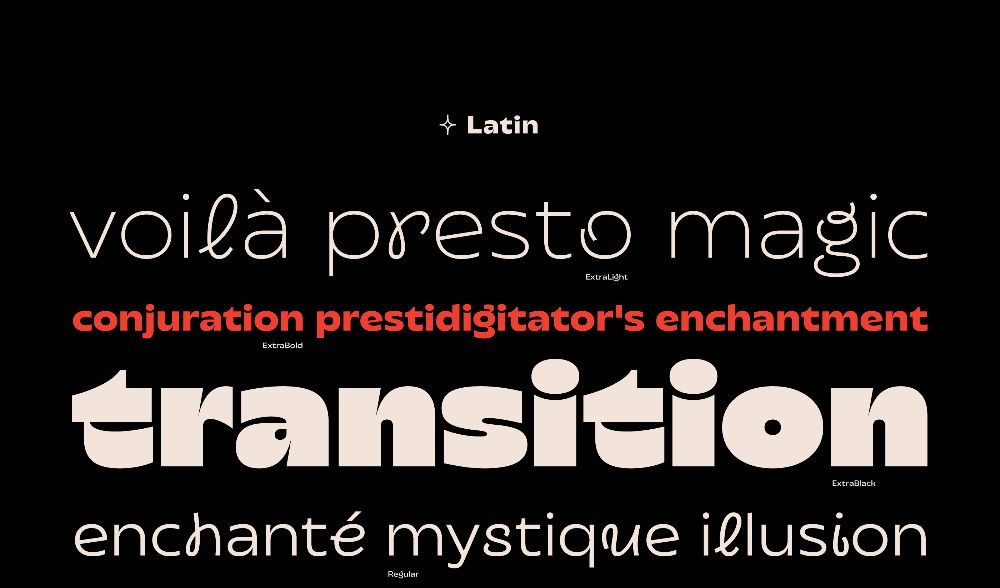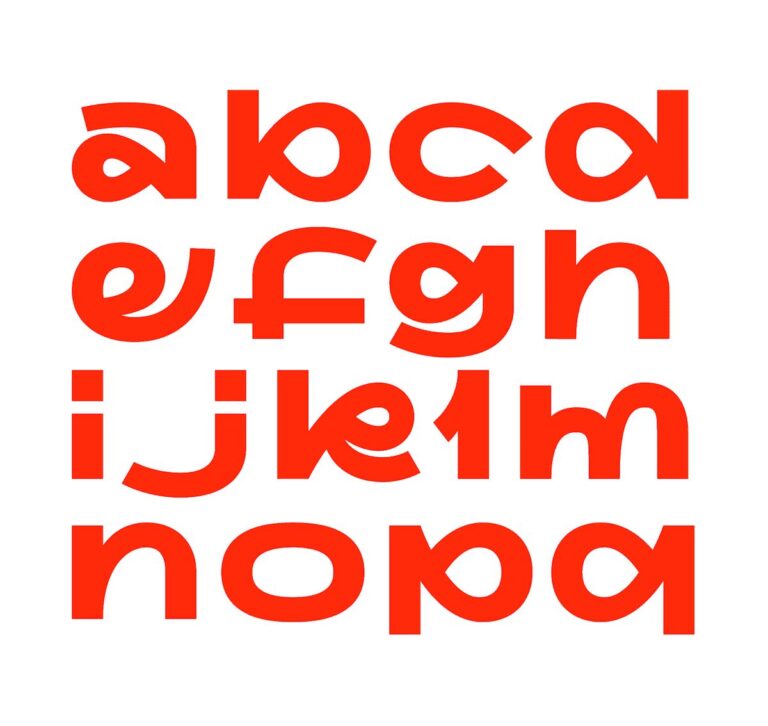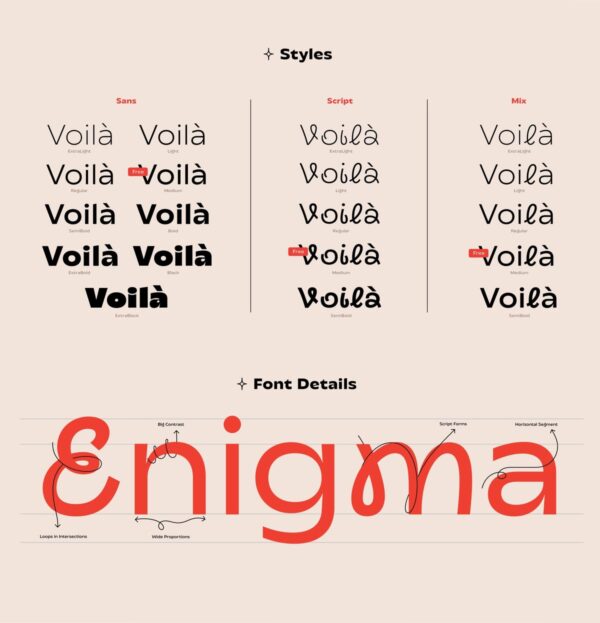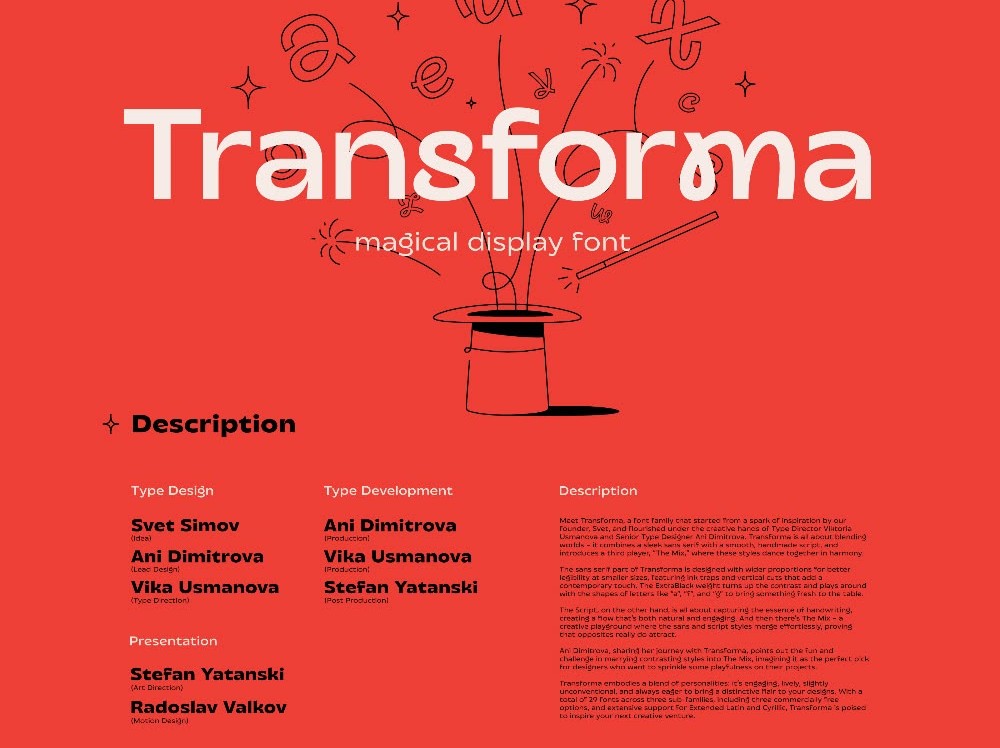
Transforma font family là một hệ thống phông chữ đồ sộ và linh hoạt, được thiết kế để đáp ứng nhu cầu sáng tạo đa dạng từ phong cách hiện đại, tối giản đến nghệ thuật bay bổng. Việc sở hữu trọn bộ Transforma font family Việt hóa giúp các kiến trúc sư và nhà thiết kế dễ dàng đồng bộ hóa ngôn ngữ hình ảnh cho các hồ sơ dự án, phối cảnh kiến trúc hay bộ nhận diện thương hiệu công trình.
Đặc tính thẩm mỹ và cấu trúc của Transforma font family Việt hóa
Điểm lôi cuốn đặc trưng của dòng phông này chính là sự tích hợp giữa nhiều nhánh phụ trong cùng một gia đình chữ, bao gồm các biến thể Sans-serif gọn gàng và các kiểu Script mềm mại. Cấu trúc của Transforma được tính toán kỹ lưỡng về tỷ lệ hình học, mang lại diện mạo vững chãi nhưng vẫn đầy tính nghệ thuật. Phiên bản Transforma font family Việt hóa đã được xử lý bảng mã Unicode chuẩn, giúp các ký tự đặc biệt trong tiếng Việt hiển thị ổn định, không gặp tình trạng lỗi dấu thanh hay nhảy chữ khi trình bày nội dung.
Sự ổn định của bộ phông này còn nằm ở khả năng tạo ra sự phân cấp thông tin hiệu quả. Nhờ dải biến thể phong phú, người thiết kế có thể linh hoạt phối hợp giữa các độ đậm nhạt khác nhau để tạo chiều sâu thị giác cho văn bản. Đây là giải pháp phù hợp để định hình phong cách cho các công trình hiện đại như nhà lắp ghép, văn phòng container hay các không gian sống đòi hỏi sự đổi mới và tư duy thẩm mỹ đồng bộ.
| Phân loại phong cách | Sans-serif / Mix Script / Modern Family |
| Nhóm phông chính | Transforma Sans, Transforma Mix, Transforma Script |
| Mục đích phù hợp | Branding, Hồ sơ năng lực, Poster, Decor nội thất |
Tư vấn lựa chọn: Hệ thống Transforma đạt hiệu quả thẩm mỹ cao khi bạn biết cách phối hợp nhánh Sans cho nội dung thuyết minh và nhánh Script cho các tiêu đề chính hoặc lời nhắn gửi. Sự tương phản giữa tính kỷ luật và nét mềm mại sẽ giúp bản thiết kế của bạn có gu thẩm mỹ riêng biệt.
03 Ứng dụng Transforma font family vào thực tế kiến trúc
Nhờ diện mạo đa năng và giàu tính thẩm mỹ, bộ phông chữ này mang lại giá trị thực tế cao trong khâu quảng bá và hoàn thiện các công trình xây dựng:
- Hệ thống nhận diện cho Homestay & Resort: Sử dụng nhánh Script của Transforma cho biển hiệu giúp không gian nghỉ dưỡng toát lên vẻ thư thái và gần gũi. Kiểu chữ này rất ăn ý khi gia công trên vật liệu tự nhiên như gỗ hoặc đá trang trí tại các khu nhà lắp ghép.
- Trình bày hồ sơ kỹ thuật và thuyết minh dự án: Độ rõ nét của nhánh Sans hỗ trợ đắc lực cho kiến trúc sư khi trình bày các thông số vật liệu panel, kết cấu thép, giúp khách hàng dễ dàng tiếp nhận các giải pháp thi công một cách minh bạch.
- Trang trí không gian nội thất hiện đại: Bạn có thể dùng font Transforma để cắt chữ nổi laser làm điểm nhấn tại phòng khách hoặc sảnh chờ văn phòng container, tạo nên một môi trường sống và làm việc đầy cảm hứng sáng tạo.
03 Lưu ý kỹ thuật để khai thác tối đa Transforma font family Việt hóa
Để khai thác hiệu quả vẻ đẹp của dòng font đa năng này mà không làm rối mắt người xem, người thiết kế nên lưu tâm một số kinh nghiệm sau:
- Kiểm soát mật độ chữ: Do Transforma có nhiều biến thể, bạn nên giới hạn sử dụng từ 2 đến 3 kiểu trong một bản thiết kế để duy trì tính đồng bộ. Việc lạm dụng quá nhiều nhánh phụ dễ khiến văn bản bị rời rạc về phong cách.
- Chú trọng khoảng cách dòng: Với các kiểu chữ Script trong bộ Transforma font family, bạn nên thiết lập khoảng cách dòng thoáng một chút để các nét uốn lượn không bị chồng lấn lên nhau, đảm bảo độ rõ nét khi in ấn.
- Lựa chọn nền màu phù hợp: Phông chữ này phát huy hiệu quả thị giác cao khi đặt trên các nền màu đơn sắc hoặc hình ảnh phối cảnh kiến trúc tối giản, giúp các đường nét hiện đại của bộ chữ được tôn vinh rõ ràng.